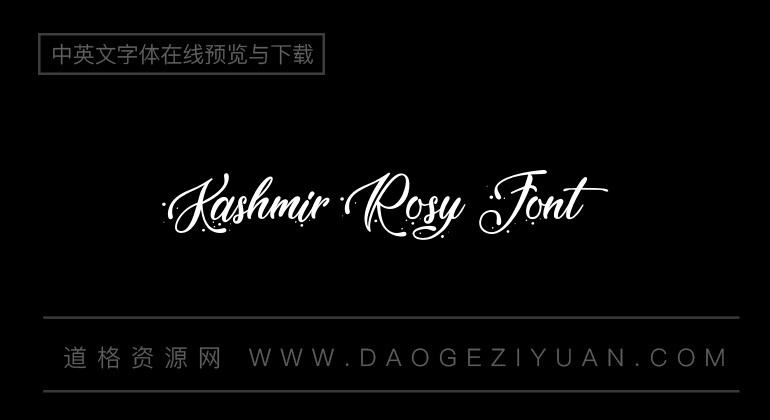
Kashmir Rosy Font是一种优美的手写风格字体,具有流畅的线条和充满个性的特点。这种字体的设计灵感来自于印度克什米尔地区的文化以及当地的艺术和手工艺品。 Kashmir Rosy Font 字体拥有印度风情的元素,如饰有印度图腾的连字、融合了印度风情的符号和装饰,给人一种印度古老文化和艺术的感觉。它的字形优美自然,适合用于各种印刷品、海报、包装设计、标志等设计作品。 此外,Kashmir Rosy Font 字体的字形非常清晰,不仅可以在屏幕上清晰显示,也可以用于打印。它的设计师注重细节和精度,使字体在各种尺寸和分辨率下都能保持清晰度和可读性。 总之,Kashmir Rosy Font 字体是一种充满艺术和个性的字体,适合用于各种设计作品,它的漂亮外观和清晰的字形使它成为了设计师们的理想选择。内容介绍
Kashmir Rosy Font是一款非常不错的手写艺术字体,具有很好的视觉感,适合于文化类的宣传设计、商业类品牌的广告和产品包装设计以及个性化文字排版等较多场景。